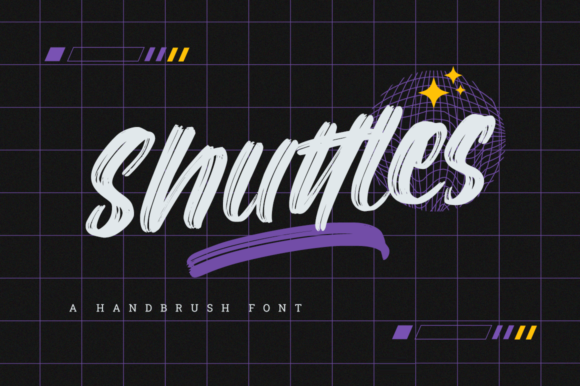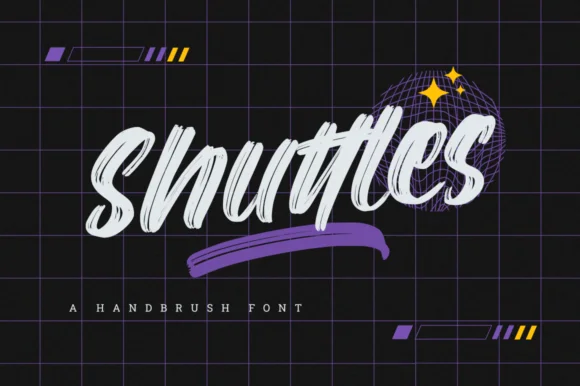
[Creativefabrica] Shuttles Font (2021)
Название: Shuttles Font (2021)
Shuttles - это крутой, смелый и матовый шрифт.
Независимо от темы, этот шрифт будет невероятно полезен в вашей библиотеке шрифтов, поскольку он способен возвысить любое творение.